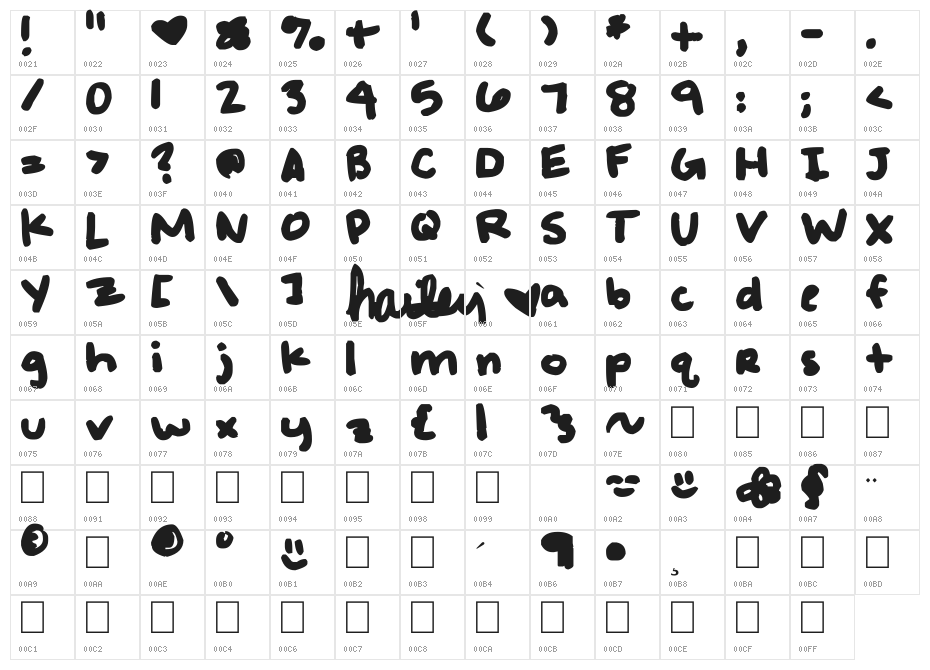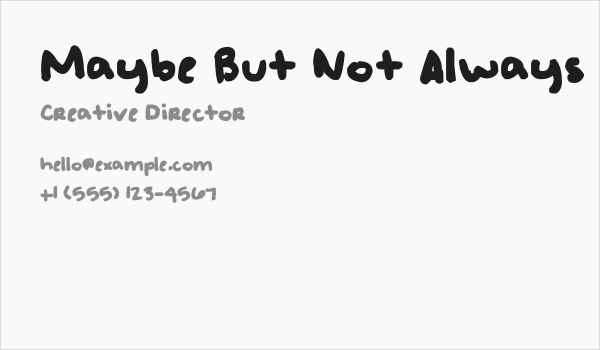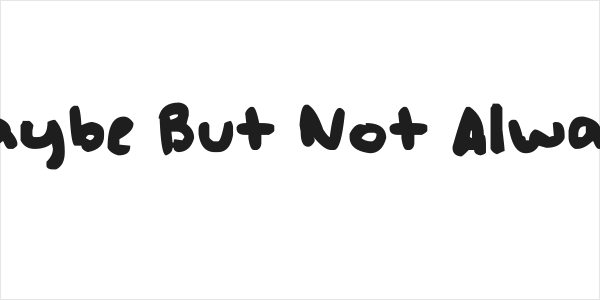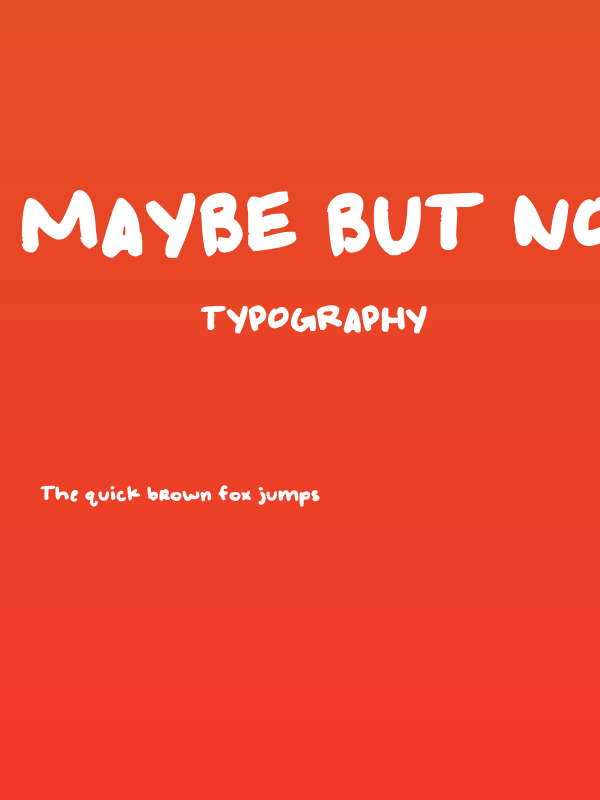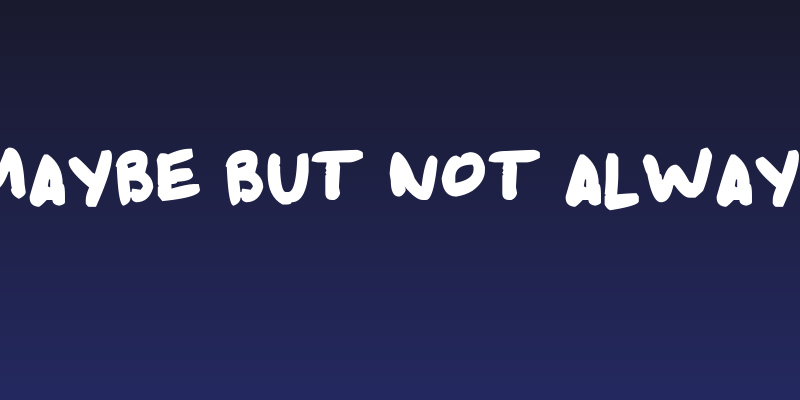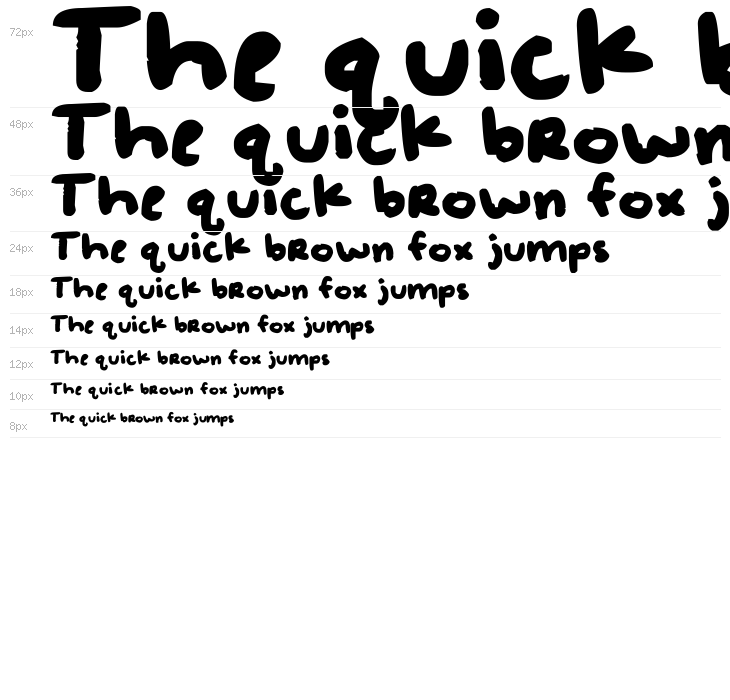
Maybe But Not Always Font
| Gesamtstil | Casual |
| Anwendungsfall | Headlines, Informal text, Creative projects |
| Vorgeschlagene Projekte | Ideal for children's books, greeting cards, casual branding, and social media graphics. |